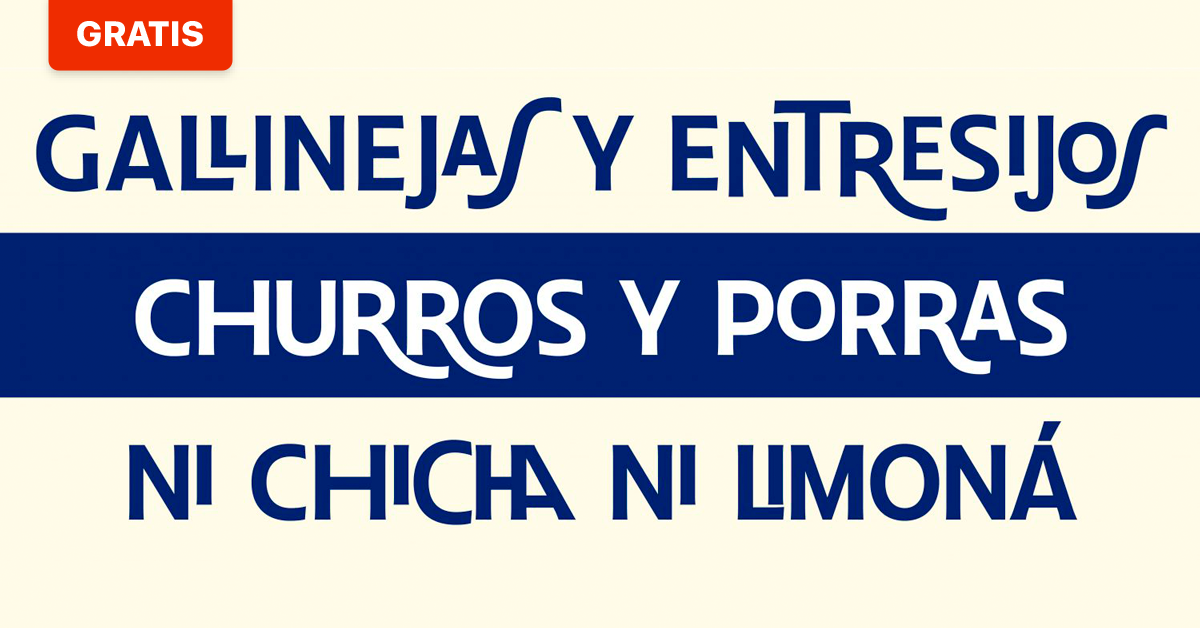
Descarga 'Chulapa', la tipografía de Madrid para el mundo
Madrid ya tiene tipografía: Chulapa, una fuente que habla de la tradición histórica y de la identidad de la capital española
Desde hace algún tiempo la ciudad de Madrid está más bonita y la causa no es solo la herencia histórica de su arquitectura o el carácter de quienes la habitan, sino por la gran apuesta del Ayuntamiento por el diseño. Las campañas publicitarias municipales han pasado a manos de un equipo creativo –con Nacho Padilla a la cabeza– que apuesta por la calidad y eso ha hecho que Madrid destaque por sus preciosos carteles que, además, son altamente efectivos.
El cartel de las fiestas del patrón local, las Fiestas de San Isidro, es uno de los más importantes del año. En 2018 la encargada de realizarlo fue Mercedes deBellard quien, con su característico estilo, sorprendió a Madrid y al mundo con una serie llena de color, flores y feminidad; ilustraciones a las que ponía la guinda la tipografía diseñada por Silvia Fernández Palomar, inspirada en los rótulos cerámicos que nombran las calles del Madrid más histórico.
El proyecto de diseño de la tipografía Chulapa está inspirado en los diseños de Juan Ruiz de Luna, el ceramista que ideó la emblemática señalización de las calles históricas de Madrid que todavía pueden encontrarse en algunos lugares de la ciudad. Esta versión de la tipografía, de palo seco no geométrico y que guarda algunas reminiscencias de la rotulación manual, ha sido producida por Joan Carles Casasín y Pablo Gámez a partir de la idea de Silvia Fernández Palomar –creadora de Ferpal Sans, la tipografía usada en el cartel de las Fiestas de San Isidro 2018 ilustrado por Mercedes deBellard–.
La tipografía contiene la esencia y la identidad de Madrid; su propio nombre, Chulapa –que es como se llama a los madrileños castizos vestidos con el traje representativo de finales del siglo XIX y principios del XX–, lo denota. Y ha sido creada para todo tipo de usos: para cada carácter existen variaciones de tamaño, ubicación o ligaduras que respetan y emulan el dinamismo y la irregularidad de la rotulación original, permitiendo crear palabras, carteles o logotipos con el carácter típico regional.
NO SÉ SI OS PASA A VOSOTROS, PERO ME HE DESCARGADO LA TIPOGRAFÍA Y NO TIENE LOS RECURSOS QUE MOSTRÁIS. LAS "S" O LAS "R" SON LETRAS DE PALO NORMALES
@alberto-22 para poder usar los caracteres alternativos de la tipografía tienes que abrir el panel de pictogramas en Photoshop (Ventana > Pictogramas) o el de Glifos en Illustrator (Ventana > Texto > Glifos). Ahí podrás ver todas las versiones disponibles de cada letra y otras ligaduras. Al menos así es como funciona en la última versión de ambos programas (si no es tu caso, busca la información en la web de Adobe, la encontrarás seguro).
Buenas tardes, he estado probando y dependiendo de la combinación de caracteres sí me salen algunas letras con rasgos, como la R, o una de menor tamaño volada sobre otra, pero no hay manera de que salga esa típica S tan estilizada y tumbada. ¿Alguien sabe cómo hacerlo? No tengo la última versión de Photoshop, así que no sé si en ventana>pictograma a la que alude Lucía Alonso se pueden visualizar las combinaciones o hay algún tipo de control para conseguir enlaces entre los caracteres y demás. ¿Puede alguien instruirme?Gracias anticipadas.